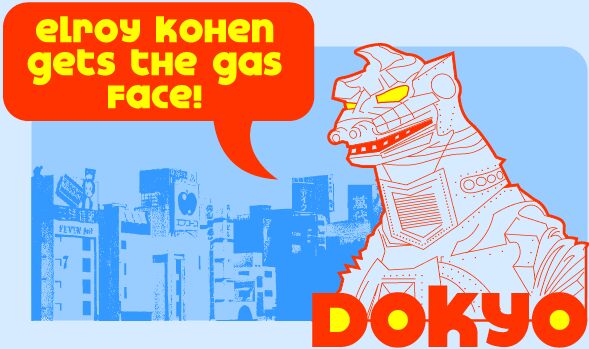
Dokyo od Fontalicious Fonts to darmowy bezszeryfowy krój pisma o śmiałej, miękkiej charakterystyce. Jego masywna geometria, okrągłe światła liter i delikatnie zaokrąglone narożniki nadają każdemu słowu zabawny, niemal gumowy charakter. Ciasny rytm między literami tworzy zwarty blok, dzięki czemu nawet krótkie nagłówki prezentują się solidnie, wyraziście i zabawnie.
Dokyo świetnie sprawdza się w przypadku zabawnych logo, opakowań słodyczy czy przekąsek, książek dla dzieci, tytułów gier, naklejek oraz wyrazistych grafik do mediów społecznościowych. Krój najlepiej prezentuje się w większych rozmiarach, gdzie jego obłe kształty naprawdę przyciągają wzrok. W mniejszych tekstach pomocniczych warto zestawić go z prostym, neutralnym krojem bezszeryfowym.